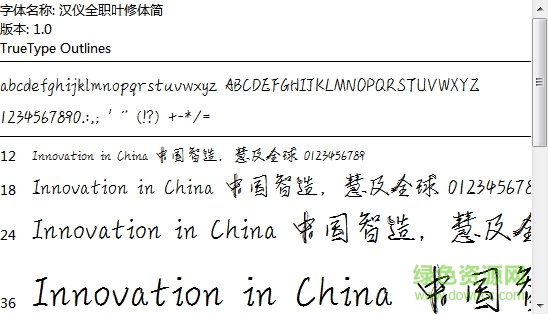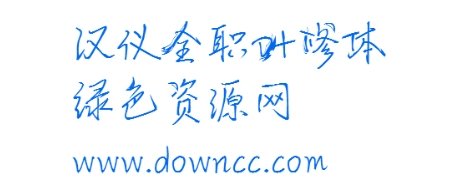
漢儀全職葉修體
漢儀葉修體是漢儀字庫專為全職高手主角葉修打造的手寫字體,全新個(gè)性裝扮讓你的字體充滿俠義之風(fēng),來綠色資源網(wǎng)免費(fèi)下載使用吧!
葉修體字帖
綠色資源網(wǎng)小編點(diǎn)評(píng)
全職葉修字體字如其人,給人連貫利落的豪杰之氣,字跡清爽散發(fā)著驕傲而凌厲的氣勢(shì),給人代入感,用于平面設(shè)計(jì)、海報(bào)設(shè)計(jì)、排版打印等多個(gè)行業(yè)